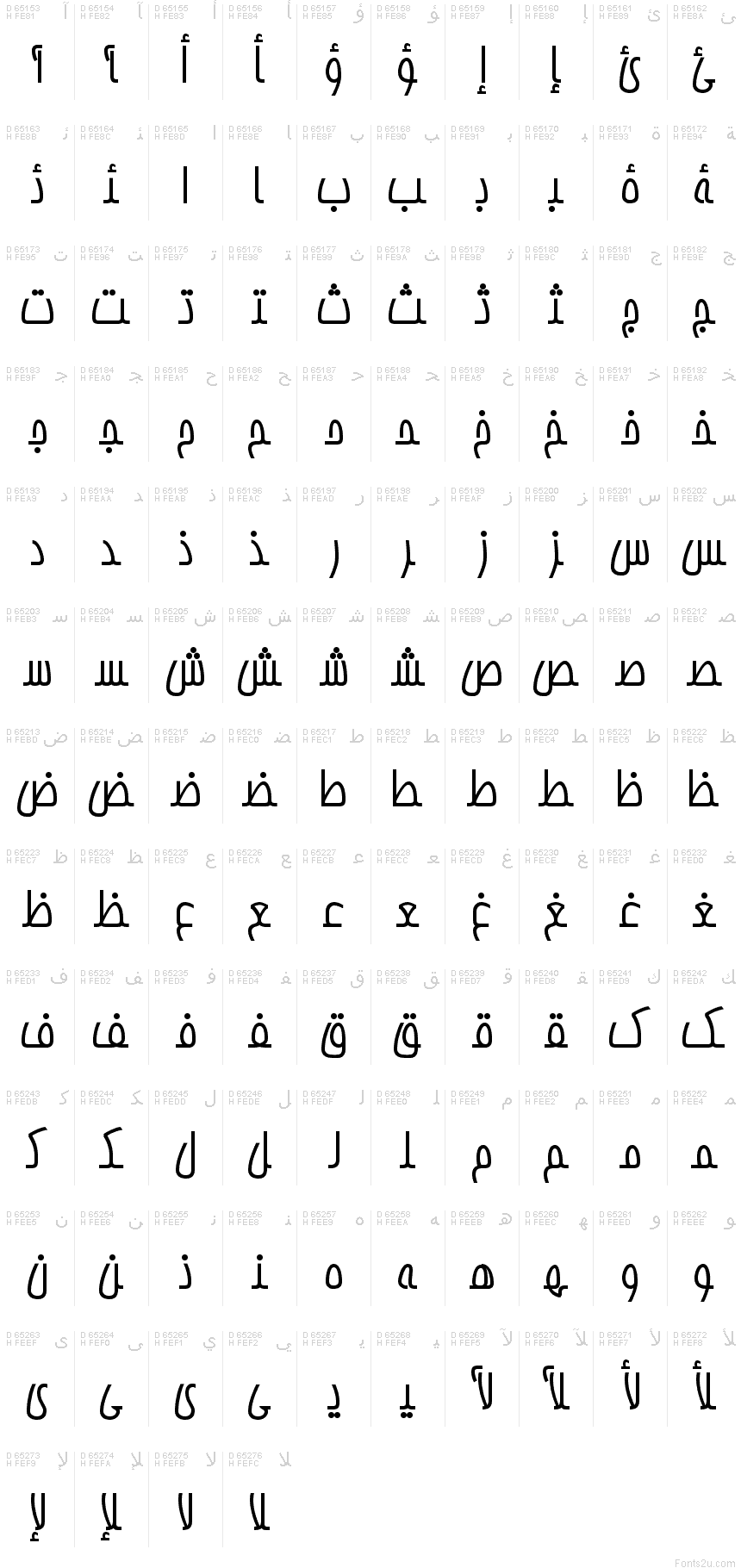
B Bardiya od Borna Rayaneh je bezplatné arabské titulkové písmo s kompaktním, kaligrafickým nádechem. Písmena působí, jako by byla vytvořena z hustých, zaoblených tahů a hlubokých křivek, což písmu dodává tmavý, důrazný rytmus. Působí spíše jako ručně kreslené titulky než jako běžný text. Hodí se na kulturní plakáty, obaly hudebních nosičů, knižní obálky, grafiku výloh či krátké redakční nadpisy, kde má bezplatné písmo s výrazným arabským charakterem vyniknout. Využijte ho při tvorbě titulků, logotypů nebo krátkých textů na obálkách, když chcete, aby písmena fungovala stejně jako výrazný grafický prvek, nejen jako text.
Mapa znaků písma B Bardiya
Mapa znaků písma B Bardiya: Arabské prezentační formy-B, strana 1
Glyfy písma B Bardiya — Arabské prezentační formy-B, strana 1